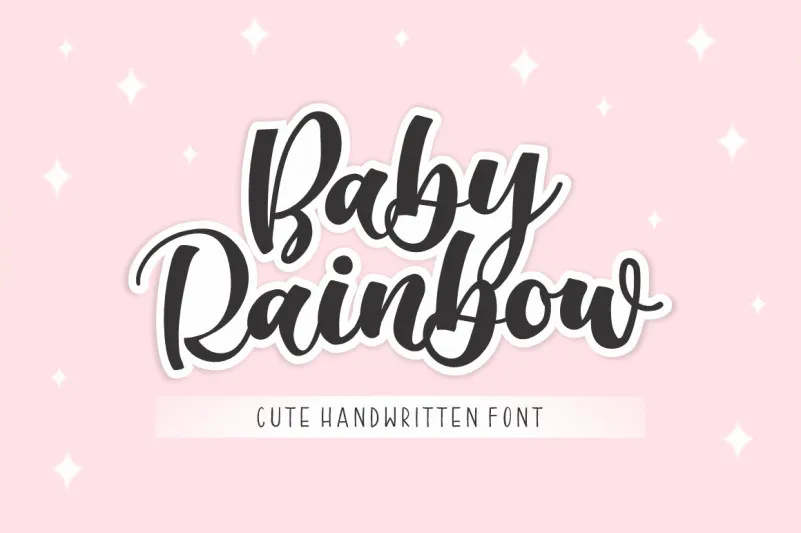
Baby Rainbow Font – Download Grátis
Esta é uma fonte feita à mão com traços círculares, perfeita para quem busca um ar doce e romântico em seus trabalhos de design. Agradável e elegante, essa fonte pode ser aplicada a uma variedade de ideias de design. Ela adicionará um toque leve e alegre aos seus projetos. A fonte Baby Rainbow é PUA codificada o que significa que você poderá acessar todos os gráficos e traços círculares com facilidade! Ideal para aqueles que buscam uma adição única de personalização em suas criações, seja um logotipo, artesanato ou até mesmo uma simples expressão. Baby Rainbow Font é a escolha perfeita para quem busca trazer vida ao seu design, sem sair da área de texto.